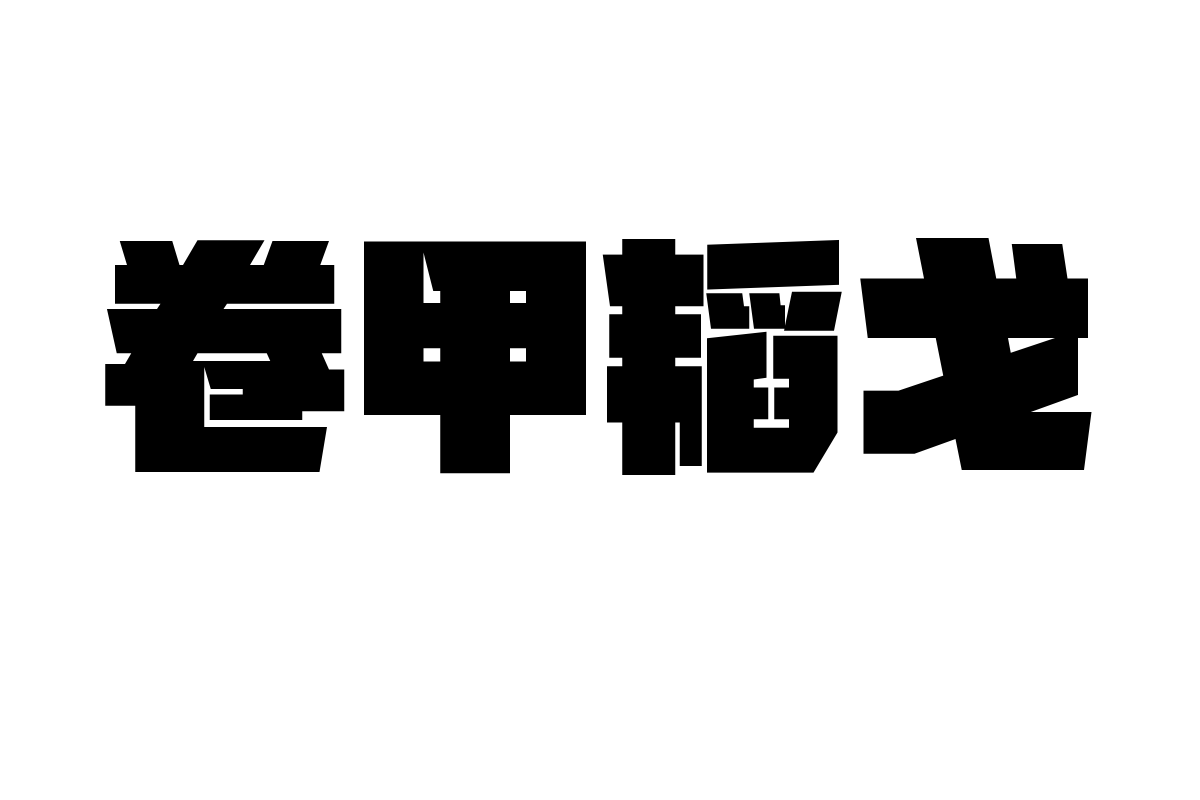
锐字潮牌雷霆超级黑是一款具有现代感的中文字体。它由锐字设计团队精心打造,采用了独特的设计风格和结构,使其在视觉上具有很高的辨识度。这款字体适用于各种商业、广告、设计等领域,能够为作品增添一份独特而时尚的气息。
锐字潮牌雷霆超级黑的特点如下:
1. 字形简洁大方:该字体采用简约的设计手法,字形线条流畅,没有过多的装饰元素,使得整体看起来更加简洁大方。
2. 结构紧凑:每个字符都经过精心设计,保持了一定的间距和比例,使得整个字体看起来更加协调和美观。
3. 易读性强:由于字形结构简单,笔画清晰,使得阅读起来更加方便,提高了文本的可读性。
4. 适应性强:无论是用于标题、正文还是广告宣传等场合,都能展现出良好的视觉效果,满足不同场景的需求。
5. 个性鲜明:该字体具有强烈的个性特色,能够吸引人们的注意,增加作品的吸引力。
总之,锐字潮牌雷霆超级黑是一款极具特色的中文字体,适用于多种场合,能够满足不同用户的需求。